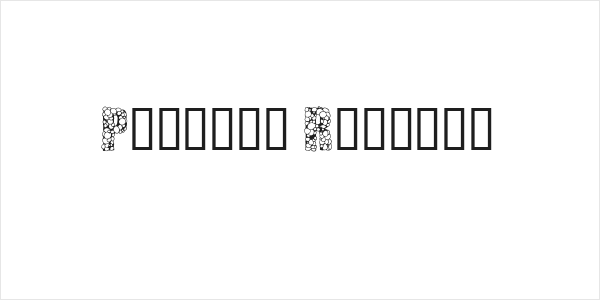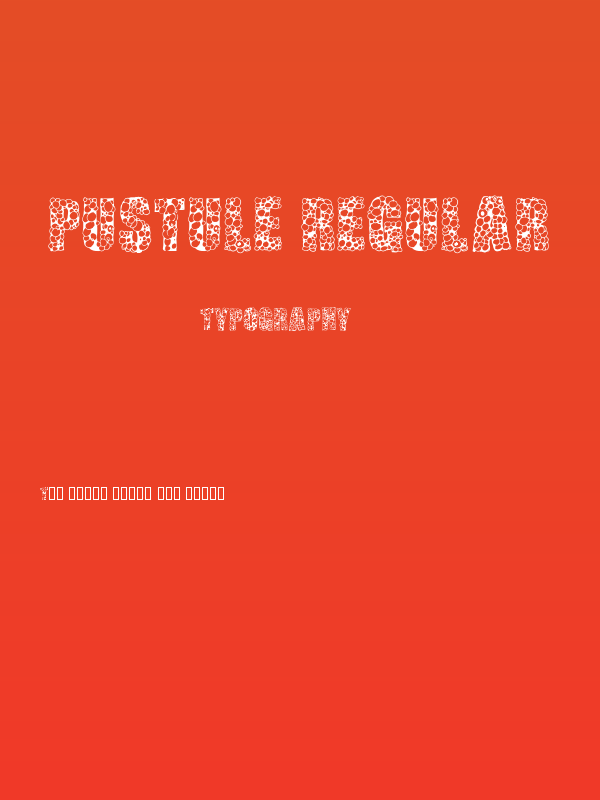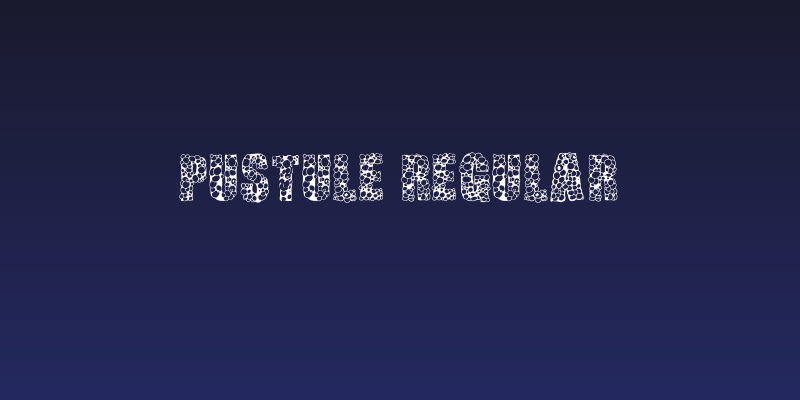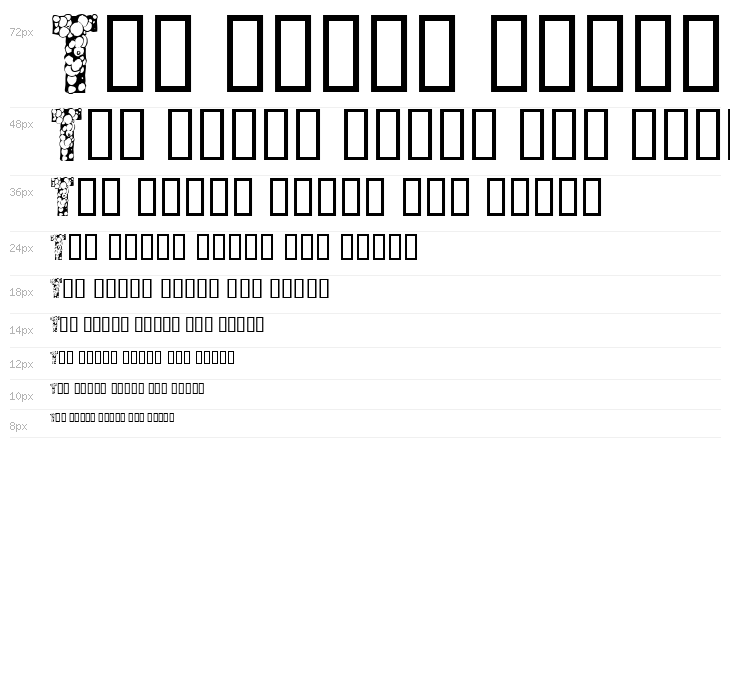
Pustule Regular Font
✎ bubble letter
| Categorie | bubble letter |
| Progetti proposti | Ideal for children's book covers, party invitations, creative posters, and branding for playful or quirky products. |